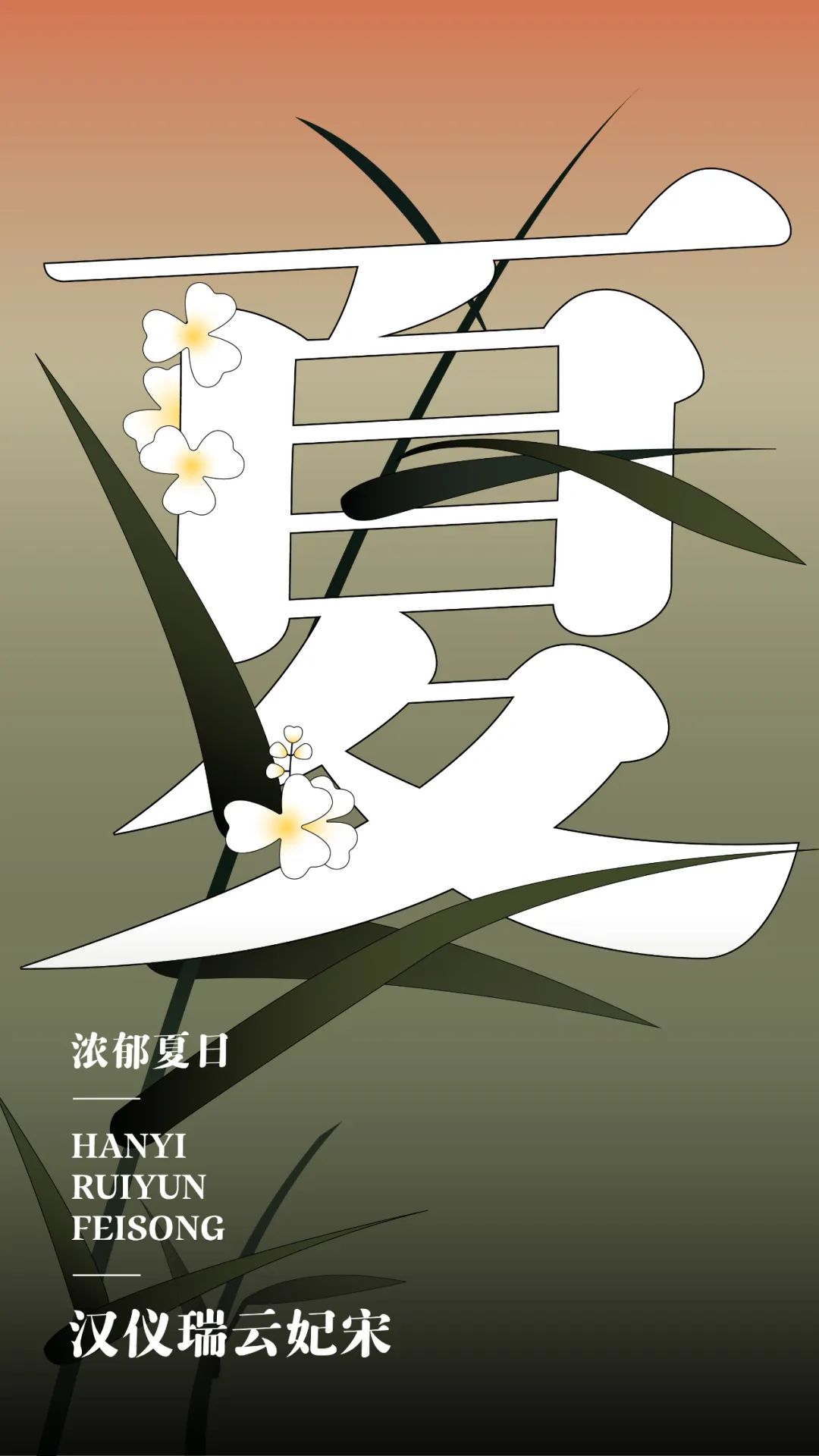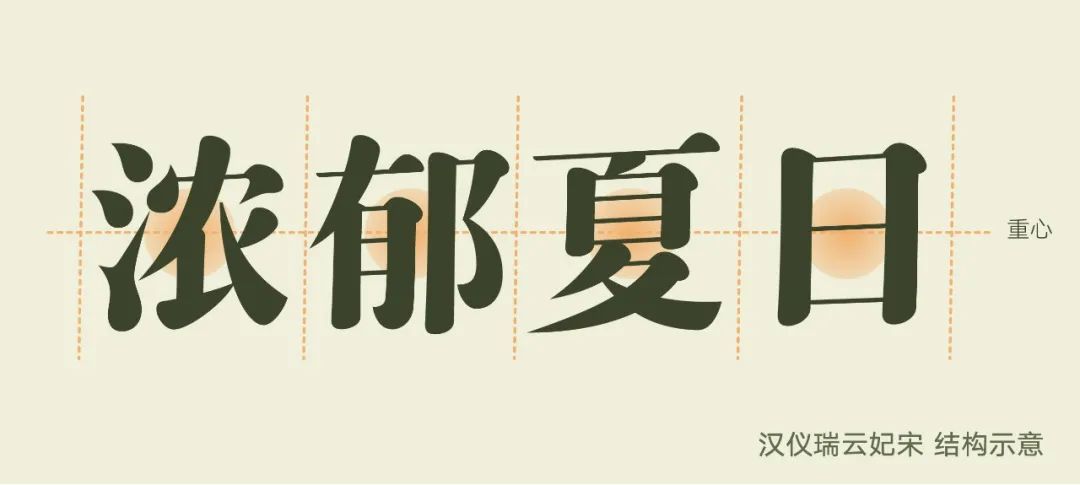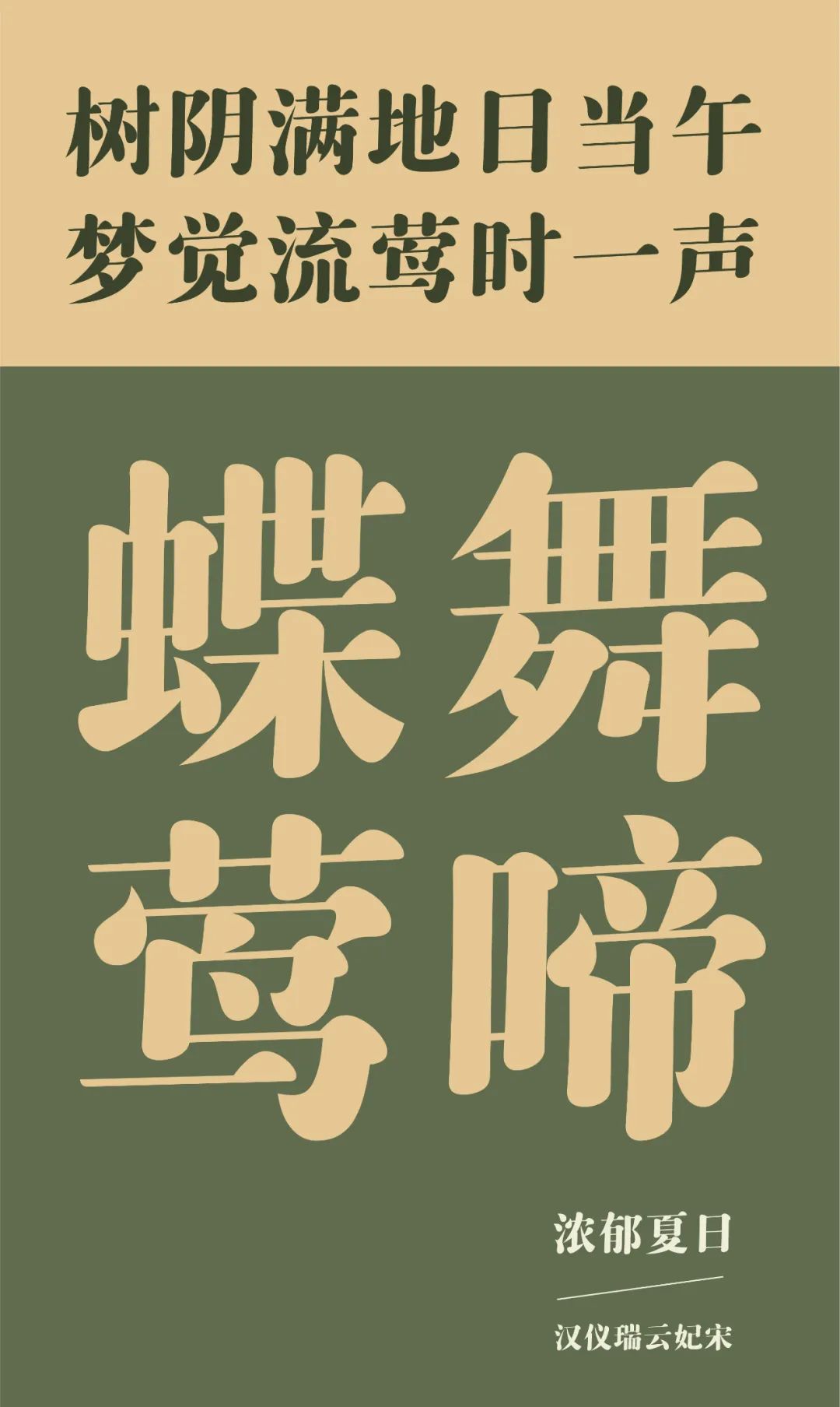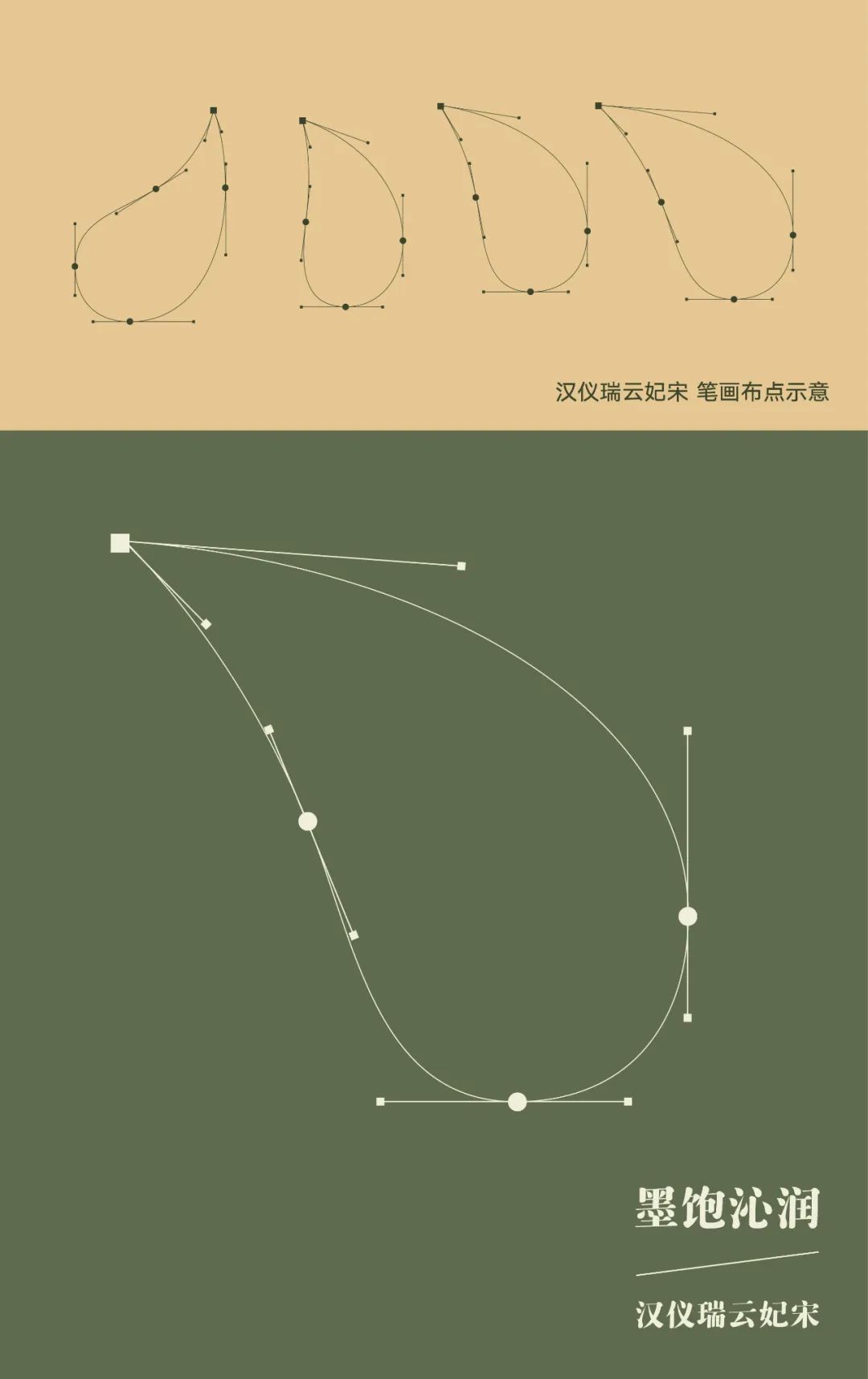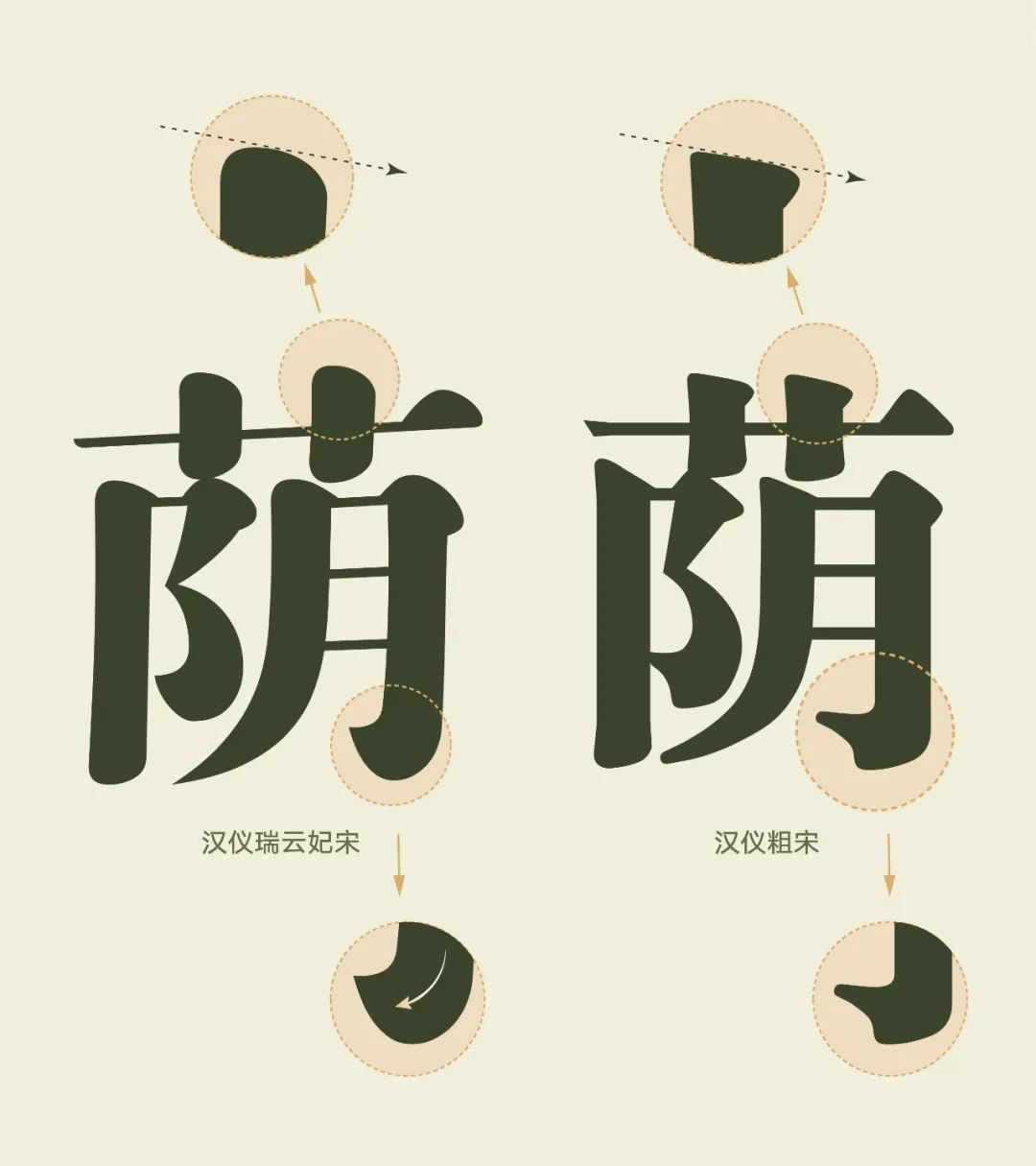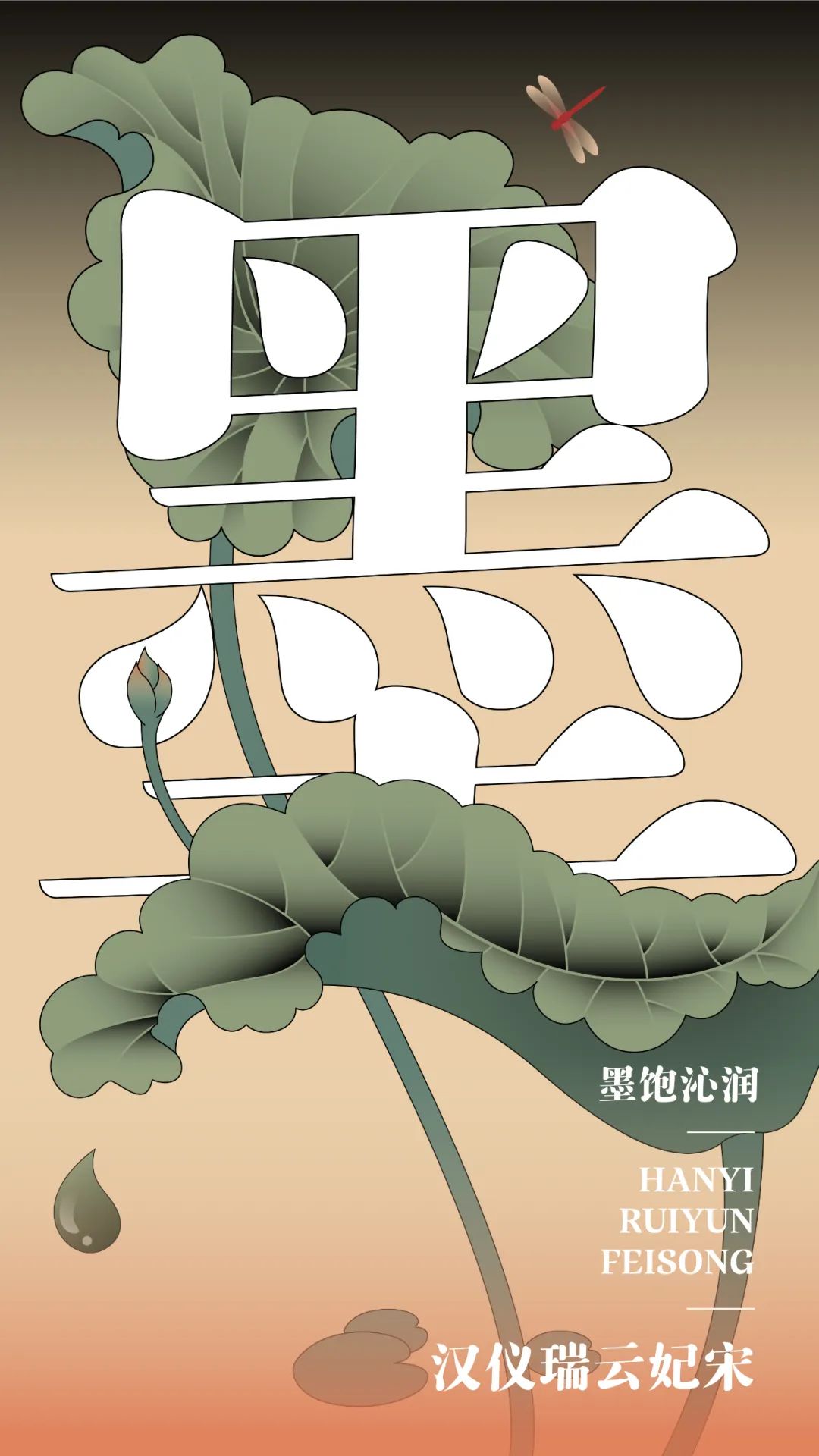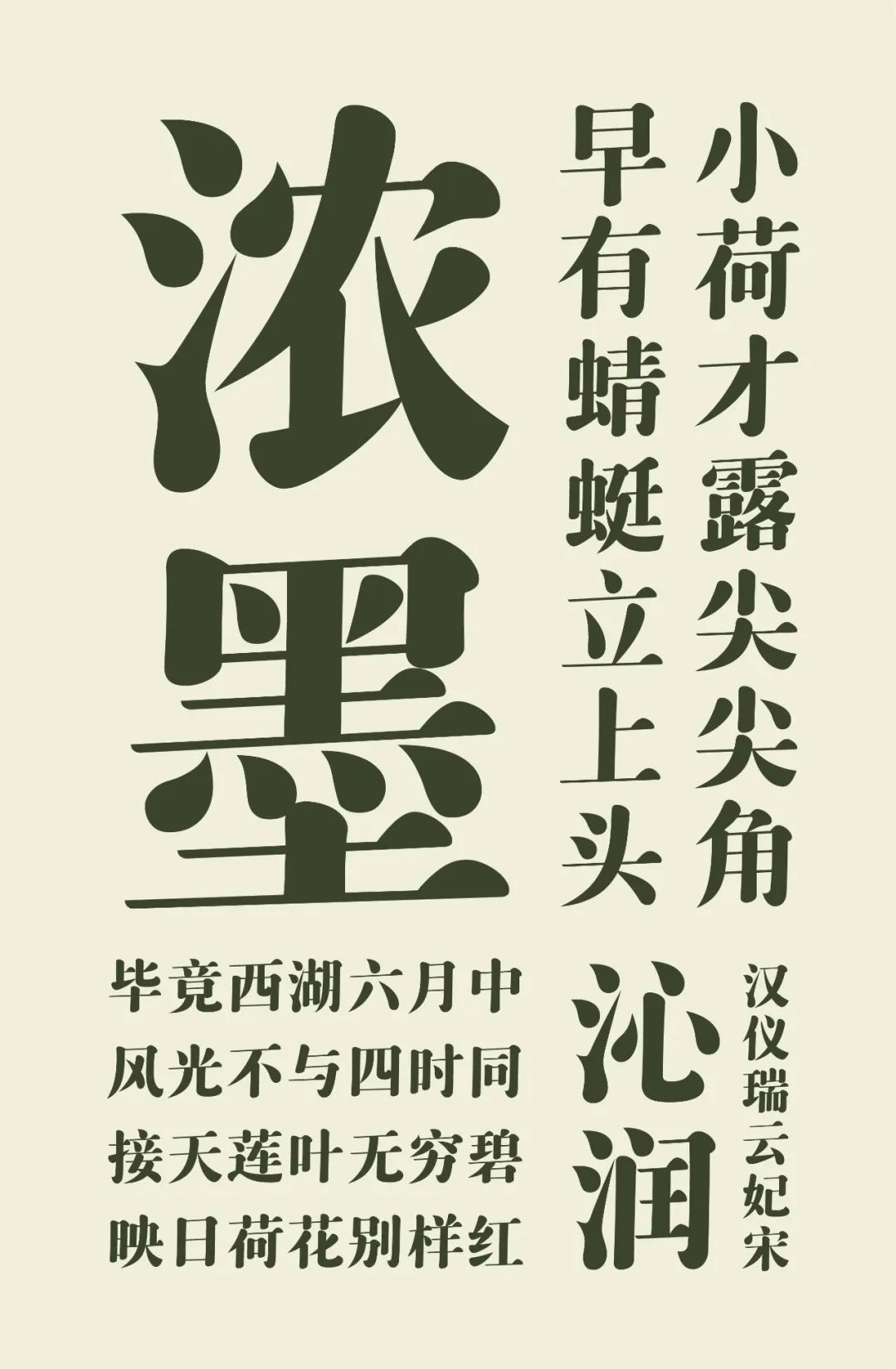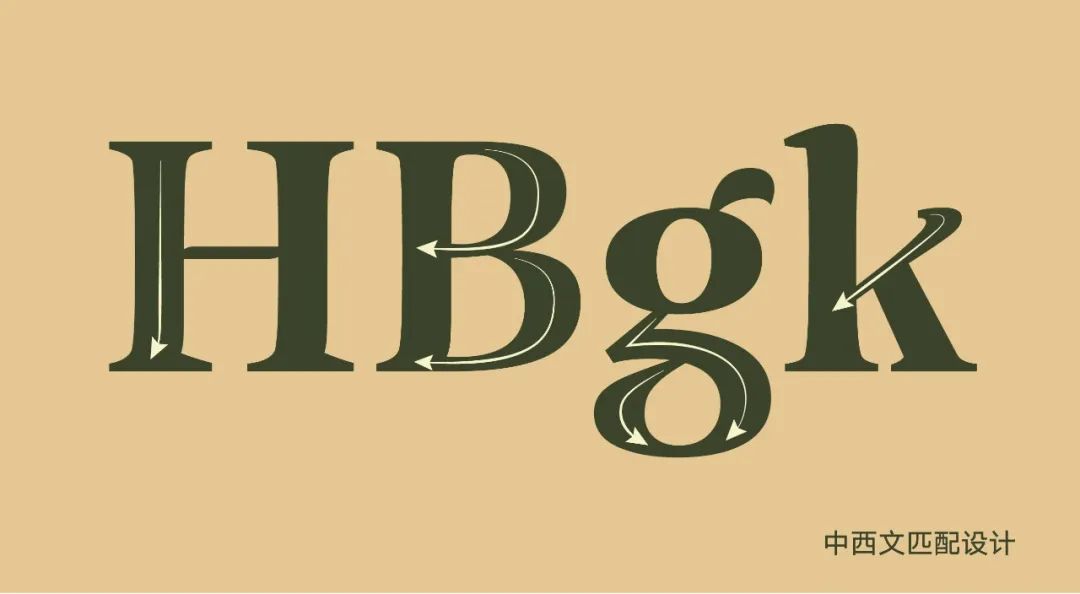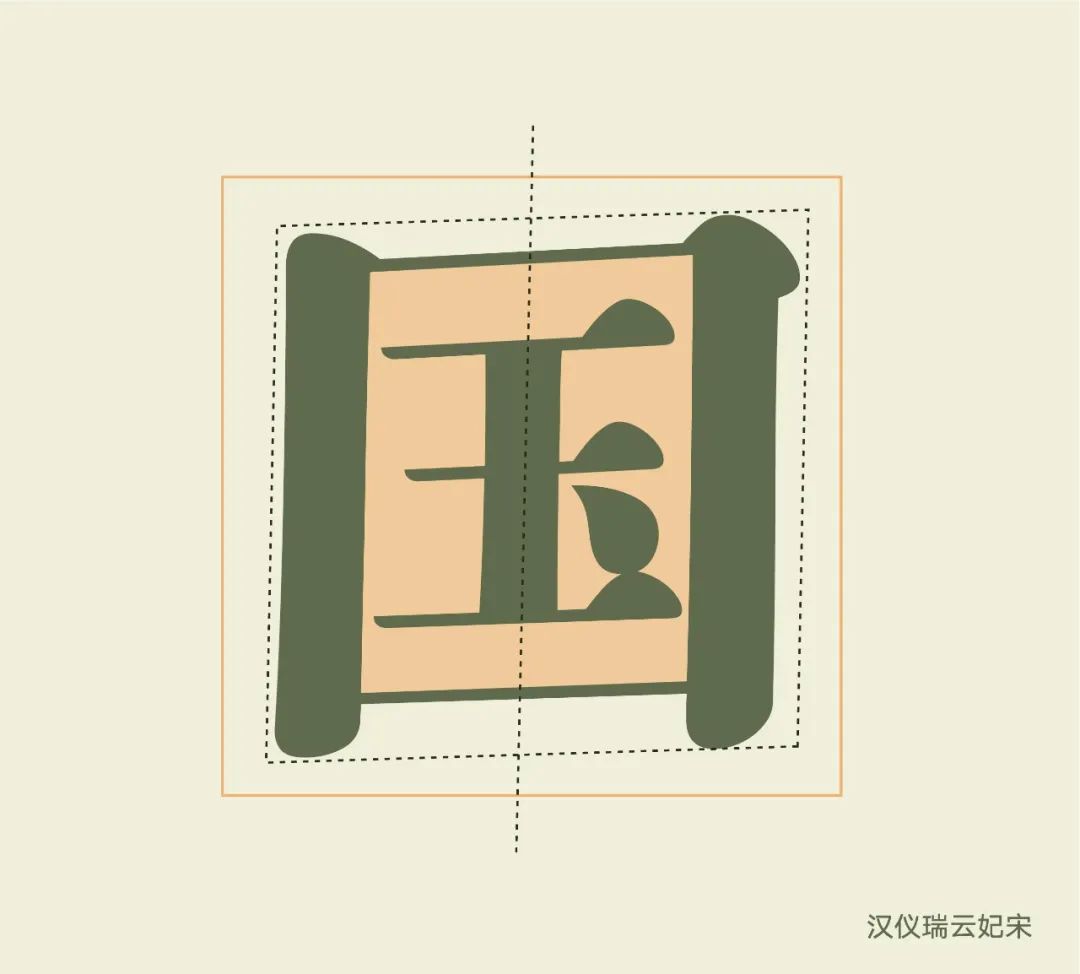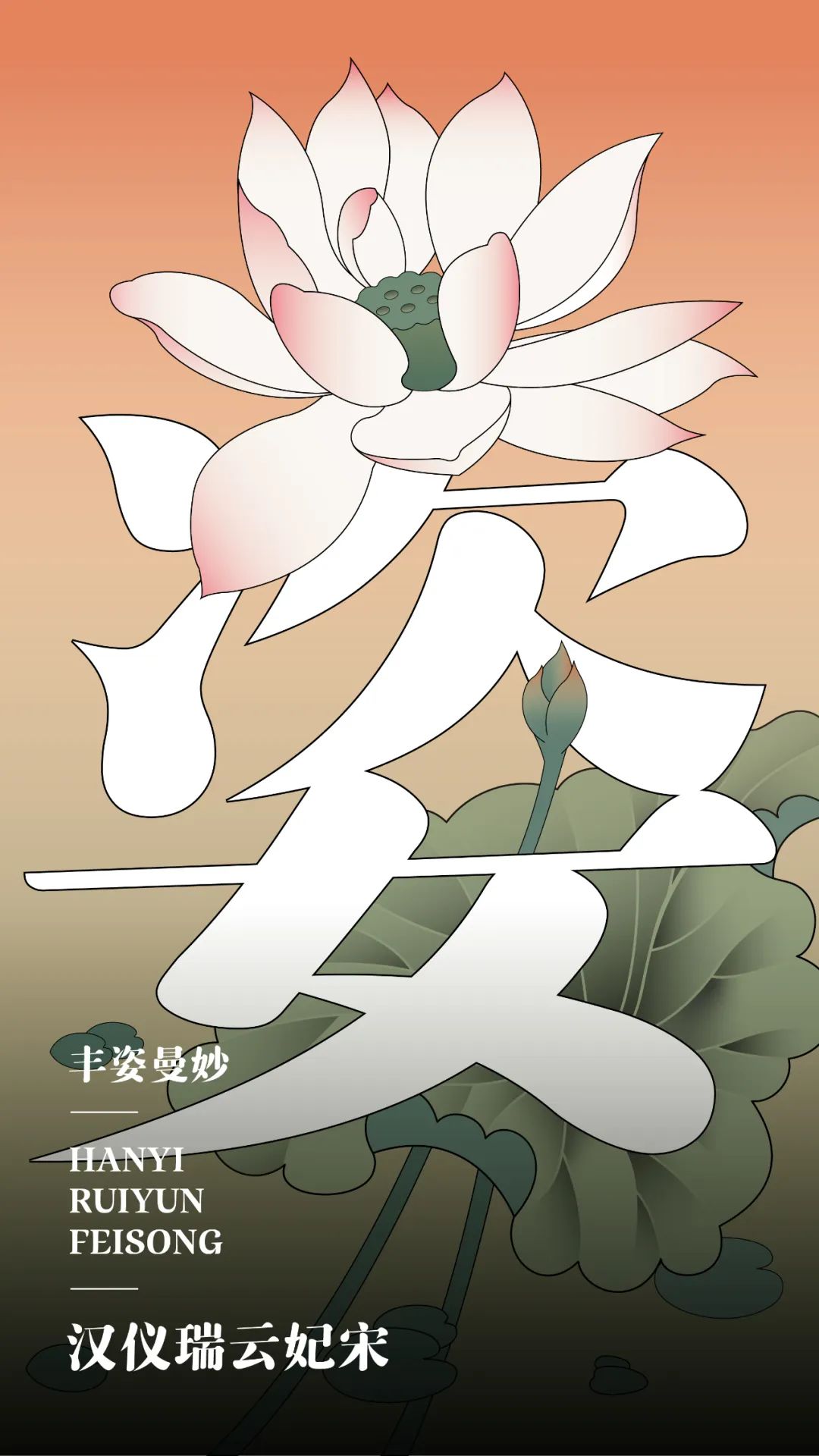
汉仪瑞云妃宋字体介绍,汉仪瑞云妃宋字体分享
汉仪瑞云妃宋是汉仪字库签约设计师战国栋继“汉仪瑞意宋”、“汉仪瑞虎宋”之后主创的第三套字库。虽然都属于宋体字,但每款字体的性格形象还是非常不同的。
“如果说汉仪瑞意宋是现代时尚、冷酷高雅的商业人士的话;那么汉仪瑞虎宋就是虎啸风生、沉稳厚重,有着强大气势的猛男;而汉仪瑞云妃宋则是体态丰腴、婀娜多姿,漫步于西子湖畔的江南美人。”
—— 战国栋
作为一款温润婉约,优雅灵动,带有人文特质的标题宋体,浓郁饱满的笔形与传统严谨的宋体结构相结合,为这款字营造出一种诗情画意的语境。
汉仪瑞云妃宋灵感来源于南方的夏日。
与北方夏日有所不同的是,南方夏日空气湿润且浓厚,气息浓郁而饱满,甚至有一丝丰腴的性感让人欣娱,那么,如果用字来表达这种感受将会是什么面貌呢?
汉仪瑞云妃宋就因此诞生。
散发着夏日气息的汉仪瑞云妃宋,结构舒展,就像是花草的枝干,叶顺势而长,花随势而开;字体曲线丰富而有弹性,生机勃勃。
汉仪瑞云妃宋的字形斜中求稳,重心一致。字形舒展放松,布白均匀,整体和谐统一,传递出优雅稳重的感觉。
这款字体的笔画弱化了宋体字起笔收笔的部分特征,处理方式更简洁柔和,曲线变化丰富,从而更好地诠释了字体想要传递的灵感。
汉仪瑞云妃宋弱化了常规宋体字笔画的刀刻感,更加强调书写感,且融入了盛夏空气湿厚的特点,使得这款字体笔墨浓重,形态丰腴灵动。
单从这款字体的点画来看,犹如荷叶上的一滴吸饱了水的露珠,圆润饱满,沿着叶子的脉络,缓缓滴落。
汉仪瑞云妃宋的西文字体造型呼应中文特点,在常规的衬线体中融入了书写特点,同时也为字体增添了趣味性。
汉仪瑞云妃宋整体结构向右微微倾斜,使得字形具有书写的流动感。笔画虽饱满但姿态灵巧,粗细对比节奏灵动,笔画舒展,丰腴曼妙。
汉仪瑞云妃宋整体结构取右倾斜势,字面为不平行四边形,左右竖线及上下横线的倾角均不平行,变中有变,也使得字体更加婀娜多姿。
汉仪瑞云妃宋的西文的中轴线微微右倾,与中文向右倾斜的视觉感觉相配,使竖直字形的西文也能有右倾的视觉感。
汉仪瑞云妃宋横笔画均有向右上倾斜的书写之势,笔画造型丰润饱满。
汉仪瑞云妃宋笔墨浓重,概括写意,形态丰腴灵动,具有人文气息。非常适用于浪漫的、温暖的、有情调的设计场景,为作品锦上添花。
主创设计师  战国栋
大连民族大学设计学院教师
SGDA深圳平面设计协会 会员
ATypI国际字体设计协会 会员
中文执行团队
汉仪珠海字研工作室
西文设计
霍悦昕